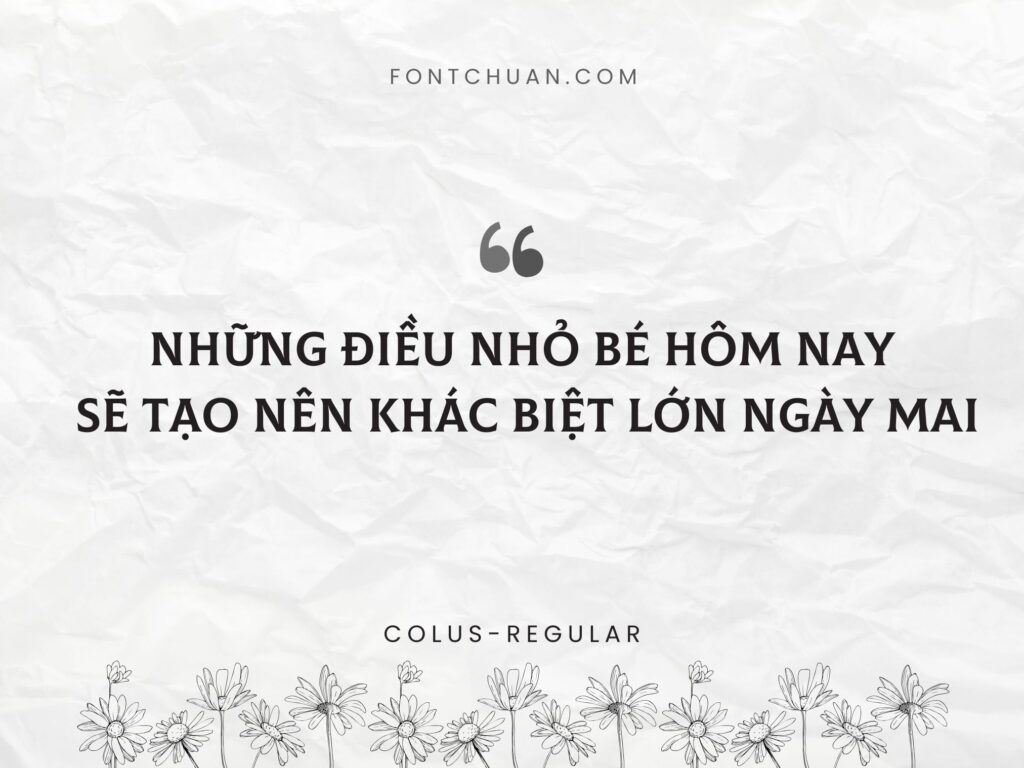
Font Colus Regular Việt Hóa
Tác giả Font: Font Fabric Free
Việt hóa bởi: Huy Nam
Colus là một phông chữ hiển thị miễn phí, được thiết kế bởi Stan Partalev và phát hành bởi Fontfabric. Lấy cảm hứng từ các chữ khắc trên đá và gỗ, Colus mang vẻ ngoài cổ điển và đặc trưng trưởng thành, phù hợp cho các tiêu đề ấn tượng, logo đáng nhớ và biển hiệu đẹp mắt. Phông chữ này hỗ trợ nhiều ngôn ngữ dựa trên hệ Latin và Cyrillic, bao gồm các ký tự đặc biệt và số liệu kiểu cũ. Colus miễn phí cho sử dụng cá nhân; nếu bạn muốn sử dụng cho mục đích thương mại, vui lòng kiểm tra giấy phép sử dụng hoặc liên hệ với tác giả để biết thêm chi tiết.
Nhờ thiết kế vừa cổ điển vừa linh hoạt, Colus cũng có thể được sử dụng như một Font chữ thiệp cưới, giúp tạo ra những tấm thiệp tinh tế, sang trọng và độc đáo. Đồng thời, với các đường nét chắc chắn và hiện đại, Colus cũng thích hợp làm Font chữ công nghệ, lý tưởng cho các dự án thiết kế liên quan đến website, ứng dụng, nhận diện thương hiệu công nghệ hoặc các sản phẩm kỹ thuật số.